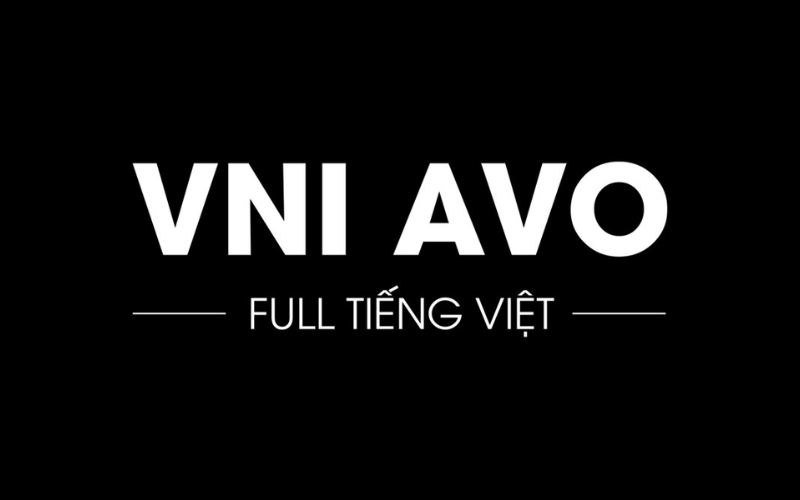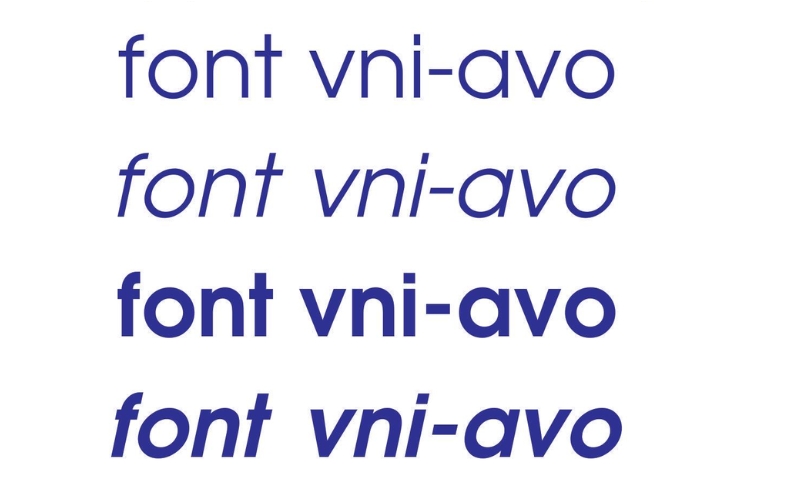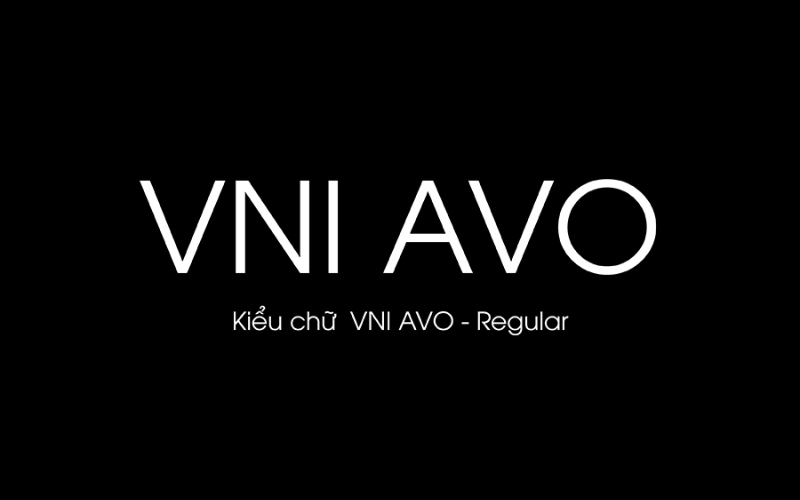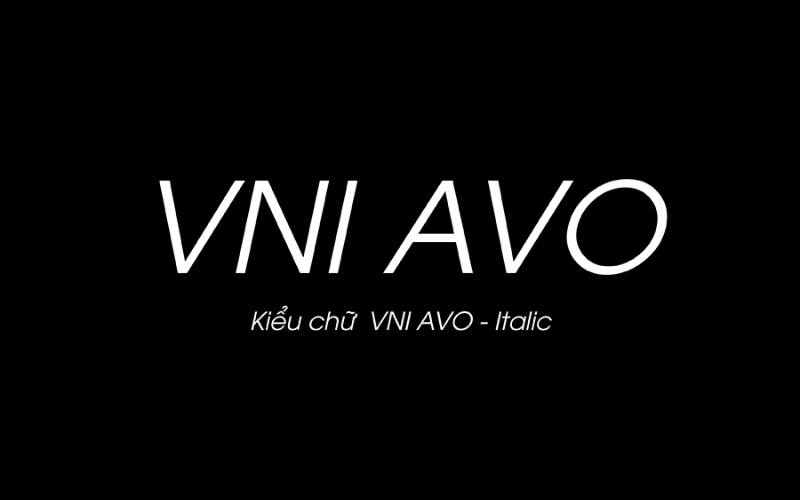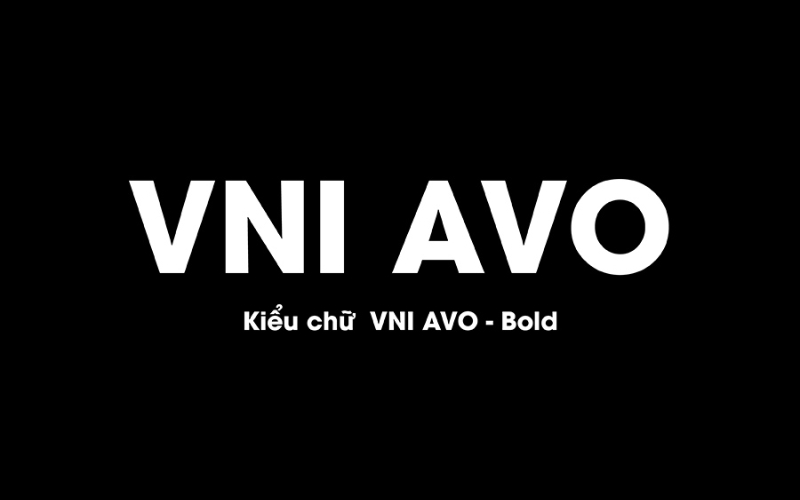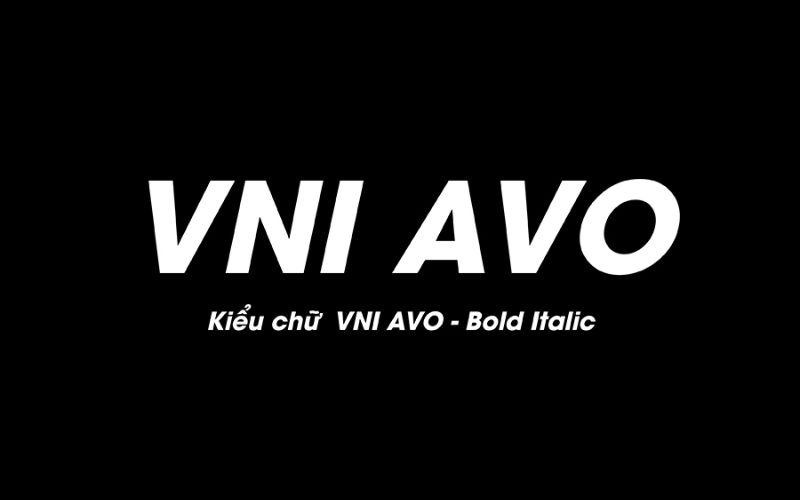
Font VNI AVO là gì?
Font VNI AVO là một trong những bộ font chữ phổ biến thuộc họ VNI, được thiết kế với phong cách hiện đại, thanh lịch và dễ đọc. Bộ font này bao gồm nhiều kiểu chữ khác nhau, từ chữ thường, chữ in hoa đến các ký tự đặc biệt, giúp người dùng linh hoạt trong thiết kế, soạn thảo văn bản, quảng cáo hay các ấn phẩm truyền thông.
Điểm nổi bật của VNI AVO là khả năng hiển thị tốt trên nhiều nền tảng và phần mềm khác nhau, từ Microsoft Word, Photoshop đến các phần mềm thiết kế chuyên nghiệp. Chính vì những ưu điểm này, việc tải font VNI AVO trở nên cần thiết đối với những ai muốn nâng cao tính thẩm mỹ và sự chuyên nghiệp trong công việc. Bộ font không chỉ đáp ứng nhu cầu sử dụng cá nhân mà còn hỗ trợ tối ưu cho các dự án thiết kế thương hiệu, banner, poster hay website.
Đặc điểm của bộ font chữ VNI AVO
Bộ font VNI AVO được nhiều người dùng yêu thích nhờ sự kết hợp giữa tính thẩm mỹ và khả năng ứng dụng đa dạng. Trước khi thực hiện cách tải font chữ VNI AVO, bạn nên nắm rõ những đặc điểm nổi bật sau để hiểu vì sao bộ font này lại phù hợp với nhiều mục đích sử dụng khác nhau.
- Thiết kế hiện đại và dễ đọc: Các ký tự trong VNI AVO có đường nét thanh thoát, cân đối, giúp văn bản trông chuyên nghiệp và dễ nhìn, ngay cả khi hiển thị trên màn hình hoặc in ấn.
- Đa dạng kiểu chữ: Bộ font bao gồm nhiều biến thể như chữ thường, chữ in hoa, chữ nghiêng, chữ đậm, giúp người dùng linh hoạt trong thiết kế và trình bày nội dung.
- Hỗ trợ ký tự đặc biệt: VNI AVO tích hợp đầy đủ các ký tự tiếng Việt, các dấu câu và ký hiệu đặc biệt, đảm bảo không gặp lỗi hiển thị khi soạn thảo văn bản.
- Tương thích cao: Bộ font hoạt động mượt mà trên hầu hết các phần mềm văn phòng, thiết kế và trình duyệt, phù hợp với nhiều nền tảng khác nhau.
- Ứng dụng đa dạng: Thích hợp cho thiết kế poster, banner, logo, website, tài liệu in ấn hay các ấn phẩm quảng cáo.
Các font VNI AVO tiêu chuẩn trong thiết kế
Để tận dụng tối đa bộ font VNI AVO trong các dự án thiết kế, việc nắm rõ các kiểu chữ tiêu chuẩn là rất quan trọng. Trước khi tải font VNI AVO, bạn nên tham khảo những biến thể cơ bản và phổ biến nhất, giúp văn bản hay thiết kế trở nên hài hòa, chuyên nghiệp. Dưới đây là các font VNI AVO tiêu chuẩn thường được sử dụng trong thiết kế:
Font VNI AVO Normal
Font VNI AVO Normal là lựa chọn phổ biến khi cần trình bày các văn bản đơn giản, dễ đọc nhưng vẫn đảm bảo sự chỉn chu. Với thiết kế tối giản, kiểu chữ này thường được sử dụng trong các tài liệu giáo dục, bài giảng, thông báo hay báo cáo, nơi nội dung cần rõ ràng và dễ tiếp nhận. VNI AVO Normal mang đến cảm giác nhẹ nhàng, dễ chịu cho người đọc, đồng thời không làm phân tán sự chú ý, phù hợp với những nội dung không yêu cầu nhấn mạnh hay trang trí cầu kỳ.
Font VNI AVO Italic
Font VNI AVO Italic mang đến vẻ mềm mại và uyển chuyển nhờ các đường nét nghiêng tinh tế. Kiểu chữ này thường được sử dụng để làm nổi bật các thuật ngữ chuyên môn, lời trích dẫn hay các từ ngữ nước ngoài trong văn bản. Mặc dù không được dùng phổ biến như VNI AVO Normal, VNI AVO Italic vẫn tạo được ấn tượng tinh tế và hiệu quả khi cần nhấn mạnh một cách khéo léo mà không làm rối mắt người đọc.
Font VNI AVO Bold
Font VNI AVO Bold là lựa chọn lý tưởng để làm nổi bật tiêu đề hoặc những thông tin quan trọng trong văn bản. Với các đường nét đậm, rõ ràng, kiểu chữ này giúp thu hút sự chú ý và truyền tải thông điệp một cách mạnh mẽ, tạo điểm nhấn cho nội dung. Tuy nhiên, khi sử dụng VNI AVO Bold, cần cân nhắc hợp lý để tránh làm rối mắt người đọc hoặc làm giảm tính cân bằng và hiệu quả của toàn bộ văn bản.
Font VNI AVO Bold Italic
Font VNI AVO Bold Italic kết hợp hài hòa giữa chữ đậm và chữ nghiêng, mang đến phong cách nổi bật nhưng vẫn giữ được sự tinh tế và thẩm mỹ. Kiểu chữ này rất thích hợp để nhấn mạnh các nội dung quan trọng hoặc những phần có thứ tự ưu tiên cao trong văn bản. VNI AVO Bold Italic thường được sử dụng trong các bài thuyết trình, thiết kế quảng cáo hoặc ấn phẩm cần tạo điểm nhấn mạnh mẽ, giúp thu hút sự chú ý của người đọc một cách hiệu quả.